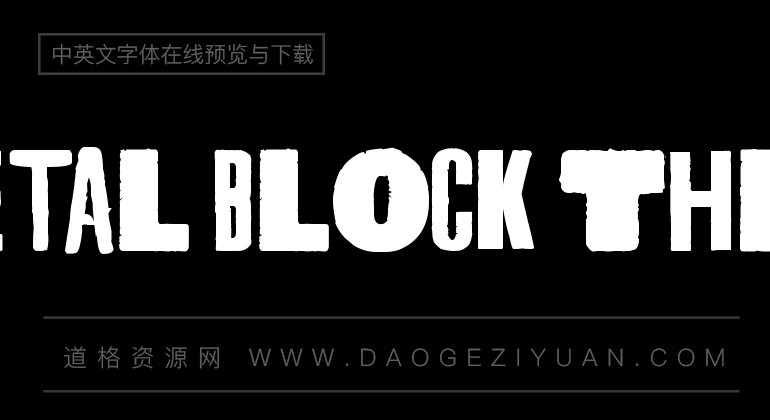
Metal Block Three 字体是一款粗体技术字体,它的设计理念来自于“机械时代”的灵感,它具有强烈的科技感,适合用于各种科技产品的标识、品牌和广告设计。Metal Block Three 字体的字体设计师非常注重细节,它的字形具有清晰的细节,使用它制作的图形和文字非常清晰,即使在小型屏幕上也能清晰地显示出来。此外,Metal Block Three 字体还具有多种字体风格,可以满足不同的设计需求。内容介绍
Metal Block Three是一款非常不错的手写艺术字体,具有很好的视觉感,适合于文化类的宣传设计、商业类品牌的广告和产品包装设计以及个性化文字排版等较多场景。